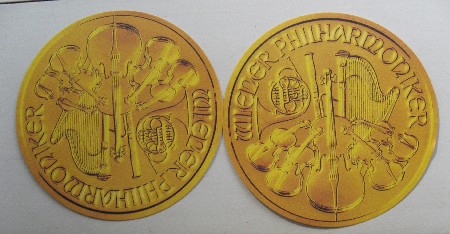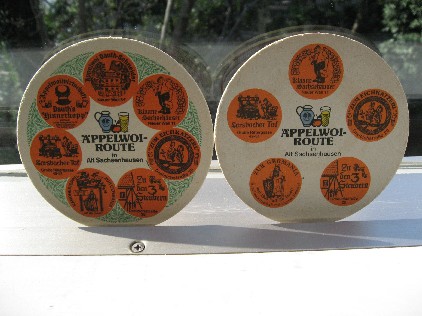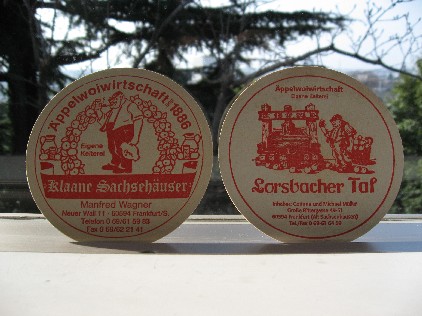
mojiな感じのコースター
普段は布地でできたコースターを使用していますが、外で
出されたコースターで可愛いデザインがありました。
7年ほど前フランクフルトにいるカリ人インゲボルグを訪ねた
際に、連れていってもらった飲み屋さんのコースターがこれ。
マイン川を挟んで南側にあるザクセンハウゼンという地域は
飲み屋さんが多いです。その時はりんご酒を飲ませてもらいました。
りんごの絵がモチーフの可愛いデザインです。
きっとお店ごとのコースターがあるんでしょうか…。
汚すのがもったえなくてお土産に持ってかえりました!
りんご酒と一緒に頂いた、チーズが美味しかったです。
確か、チーズの上に刻んだ玉葱がのっていてビネガーが
かかっていました。
国内でのヒットだと思うのは、印刷博物館で売られている
グーテンベルグがモチーフのコースター!
これならいつでも入手できるので、お友達が来たときに
気軽に使えますね。
カリ人さんへのプレゼンとにもいかがでしょうか〜。
この金ぴかは、今オーストリア航空に乗ると最初に出される
飲み物と一緒に出されるコースターです。紙はペラペラなんですが、発行されている金貨のデザインをそのまま使用という
大胆な発想です!アンシャル調のアルファベットもおしゃれで、
音楽のイメージと合っています。これもお持ちかえりしてしまいました。
最後は、ちょっと変り種。mojiな感じからは外れますが…。
これはボストンにいた時にアンティーク屋さんで見つけたもの。
ワイングラスの底にはめて使うように出来てます。
ワイン通でもない…お酒もそんなに飲めない…のに、あまりに
美しかったので(値段も安かった)、飾りにと買ってみたものです。
しかし、我家にあるグラスにはちょっと窮屈…でした。
でもどんなご婦人がその昔に作ったのでしょうねぇ〜。
みなさんはお気に入りのコースターってありますか?